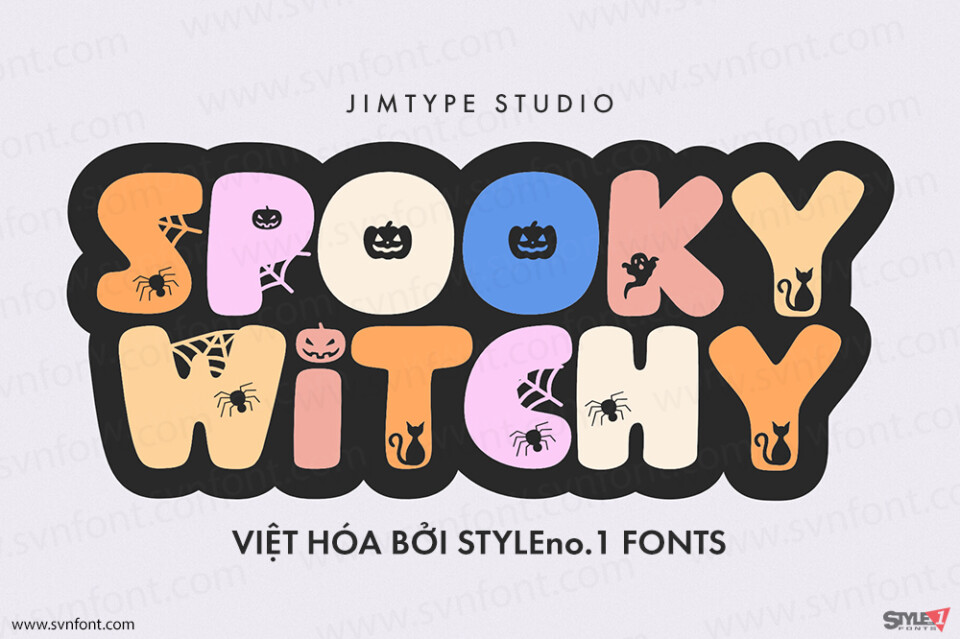
Font Việt hóa SVN Spooky Witchy
Tải Font Việt hóa SVN Spooky Witchy Miễn Phí Cho Thiết Kế Halloween
Giới thiệu về Font Việt hóa SVN Spooky Witchy
Khi mùa lễ hội hóa trang đến gần, nhu cầu tìm kiếm các mẫu Font Miễn Phí mang phong cách ma mị ngày càng tăng cao. Font Việt hóa SVN Spooky Witchy là một lựa chọn hoàn hảo dành cho những ai muốn tạo ra bầu không khí huyền bí và rùng rợn. Với các đường nét uốn lượn đặc trưng, bộ phông chữ này mô phỏng hình ảnh những chiếc chổi bay và tà áo của phù thủy, giúp các dự án sáng tạo trở nên sống động hơn bao giờ hết.
Tại sao nên chọn Font Việt hóa SVN Spooky Witchy?
Bộ chữ này không chỉ đẹp mắt mà còn được tối ưu hóa hoàn toàn cho tiếng Việt, giúp người dùng không còn lo lắng về lỗi hiển thị dấu. Điều này cực kỳ quan trọng đối với các bạn học sinh và giáo viên khi thiết kế thiệp mời hoặc trang trí bảng tin nhà trường. Font Việt hóa SVN Spooky Witchy sở hữu các ký tự độc đáo, vừa mang tính nghệ thuật vừa đảm bảo độ nhận diện tốt trên nhiều nền tảng khác nhau.
Ứng dụng thực tế của phông chữ trong giáo dục và thiết kế
Việc sử dụng Font Việt hóa SVN Spooky Witchy giúp các bài thuyết trình về chủ đề văn hóa phương Tây trở nên lôi cuốn hơn. Các em học sinh có thể dùng phông chữ này để làm báo tường, thiết kế bìa sách hoặc tạo ra những biểu ngữ chào mừng lễ hội Halloween đầy ấn tượng. Nhờ sự linh hoạt, bộ font này dễ dàng kết hợp với các hình ảnh minh họa như bí ngô, con dơi hay mạng nhện.
Để tận dụng tối đa vẻ đẹp của Font Việt hóa SVN Spooky Witchy, bạn nên sử dụng trong các tiêu đề lớn hoặc câu trích dẫn ngắn. Tránh dùng cho các đoạn văn bản dài để đảm bảo người xem không bị mỏi mắt. Với định dạng tương thích cao, bạn có thể dễ dàng cài đặt vào máy tính và sử dụng ngay trên các phần mềm soạn thảo văn bản thông dụng.